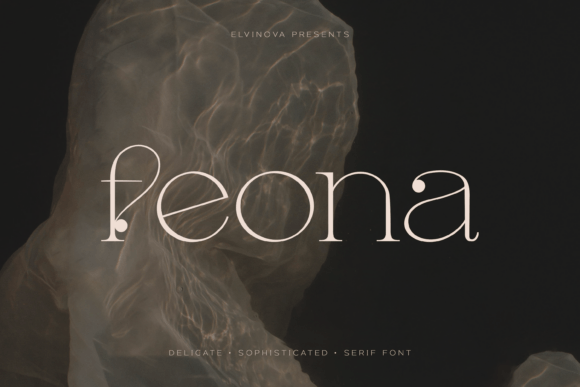
Feona Serif
適切なデザイン要素を見つけるのは難しい場合がありますが、Feona Serifは作品を即座に引き立てる優れたコレクションを提供します。
精密に作られたFeona Serifは、クリーンなベクター、滑らかなタイポグラフィ、そして安心のための商用ライセンスを提供します。
POD(オンデマンド印刷)製品、結婚式の招待状、またはソーシャルメディアのグラフィックを作成している場合でも、Feona Serifは理想的です。